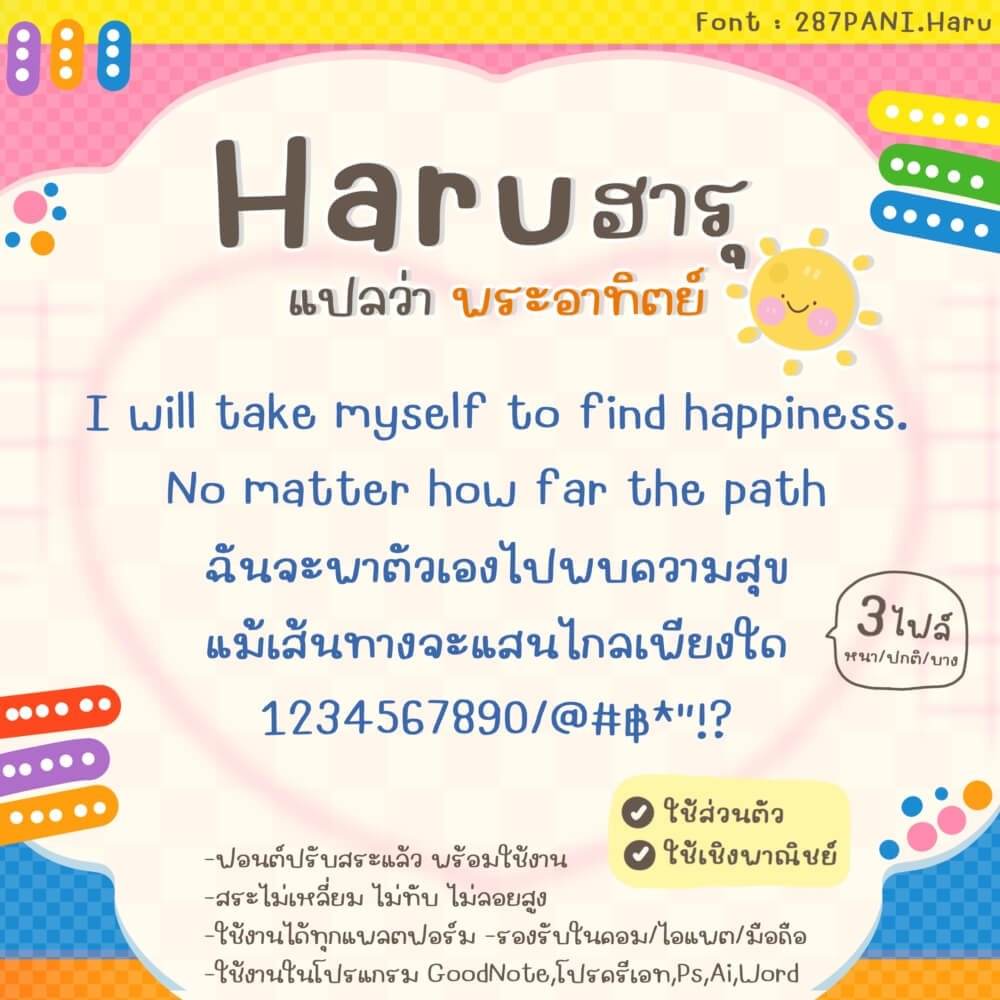
ฮารุ (287PANIHaru)
แจกฟรี 1 น้ำหนัก (สำหรับใช้งานส่วนตัว) ฟอนต์ตัวกว้างๆ อ่านง่ายสบายตา มีความเป็นวัยรุ่น น่ารัก และชุดนี้ไม่เหมือนใคร ไม่มีคำว่าเชยแน่นอน!! จะตั้งเครื่อง/อ่านรายละเอียด/แต่งภาพ คุมโทนเอาอยู่หมด แนะนำค่า